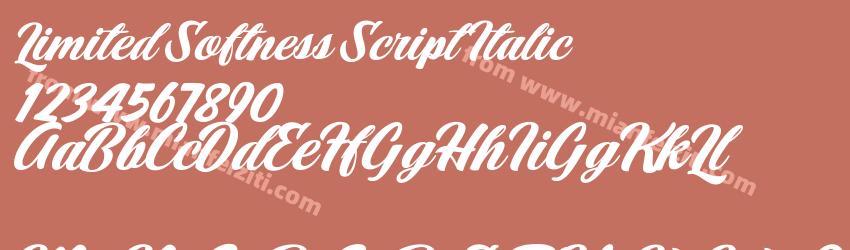
Limited Softness Script Italic
字体名称: Limited Softness Script Italic
Postscript名称: LimitedSoftnessScriptItalic
本款“Limited Softness Script Italic”是一款书写很新颖的字体,字体大方,适合各种设计作品使用!欢迎下载!